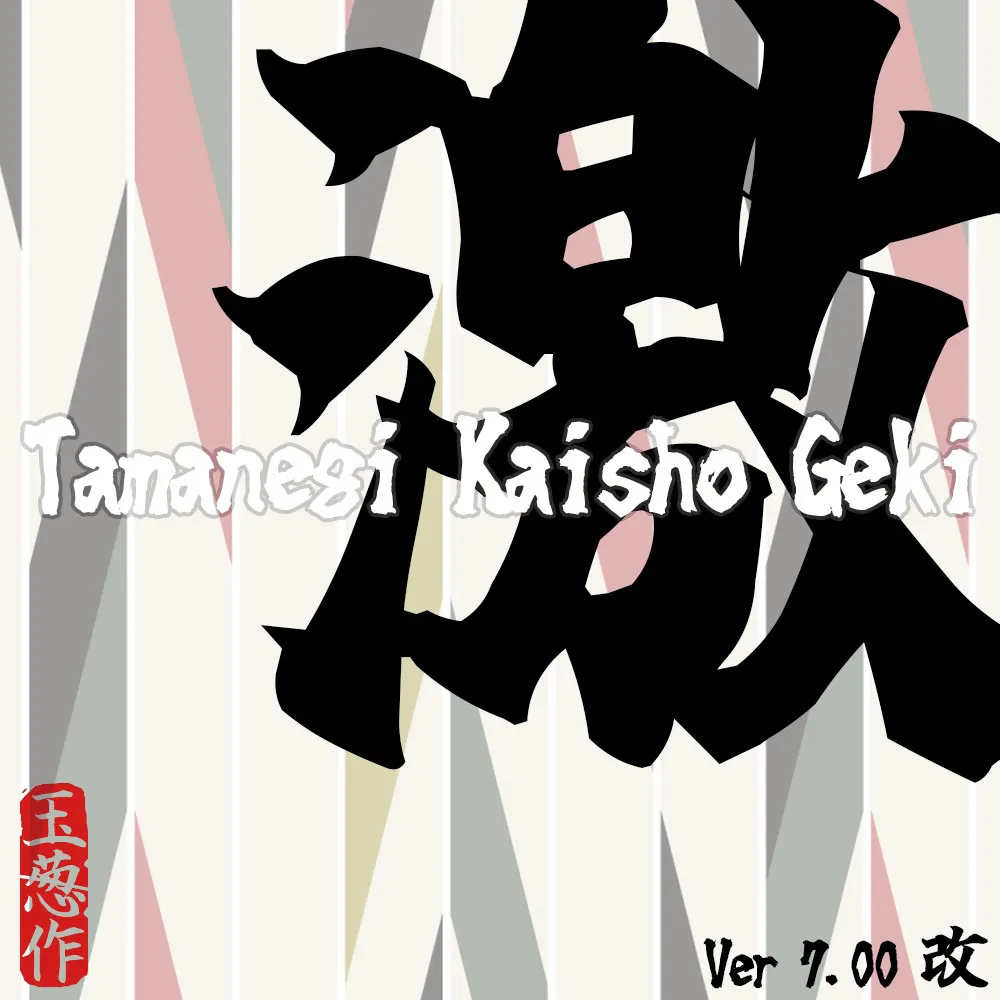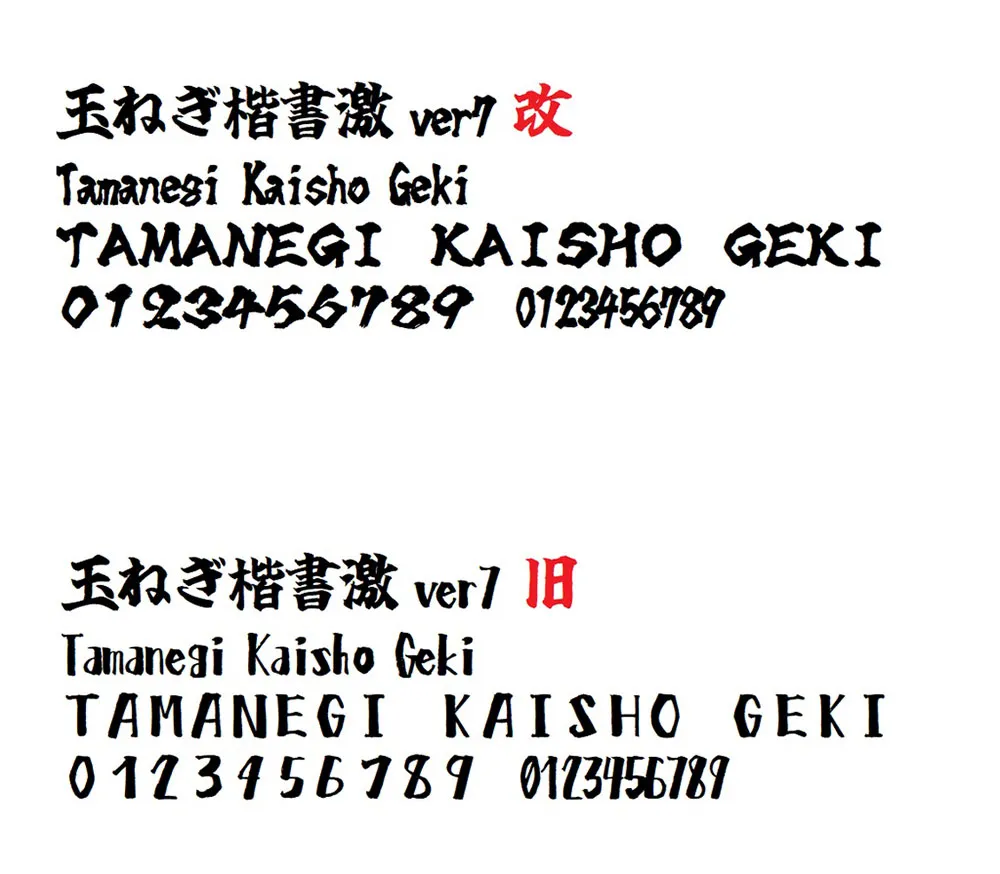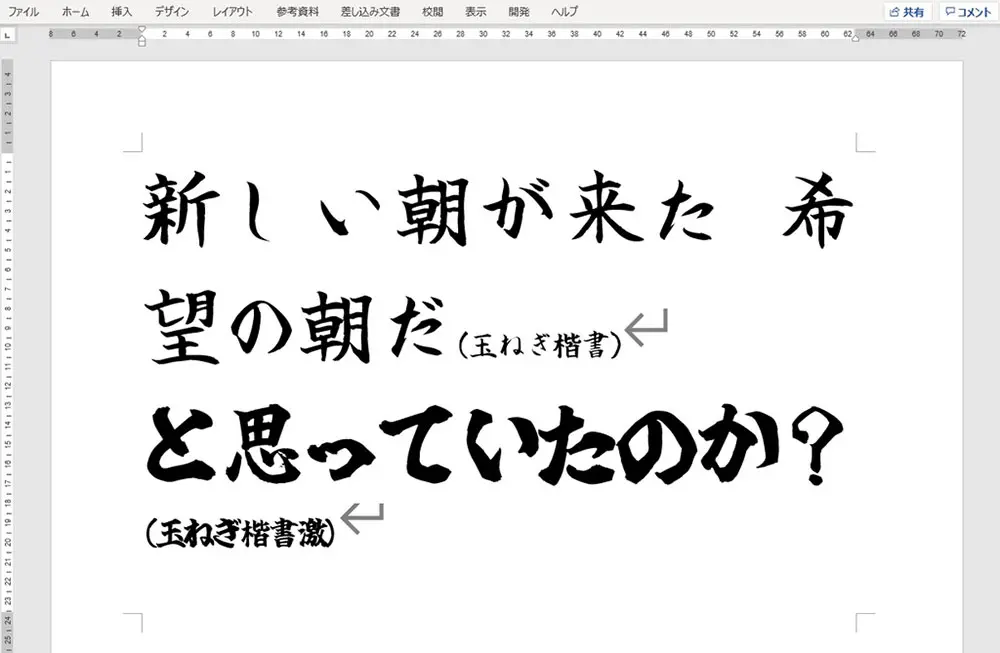
玉ねぎ楷書激無料版介紹
玉ねぎ楷書激無料版是通過使用武藏系統 (http://opentype.jp/) 的手寫字體創建的。是為動畫、同人誌、賀年卡等場景製作的簡單手寫毛筆字體洋蔥楷書(ttf形式)有點激烈。
這個字體是免費版(JIS第一水準漢字+α),目前正在製作JIS第二水準對應版。
本ファイルは武蔵システム(http://opentype.jp/)の 手書きでフォント を使って作成しました。動畫・同人誌・年賀狀などあらゆる創作の場面を想定して作られたシンプルな手書き毛筆フォント玉ねぎ楷書(ttf形式)をちょっと激しくしたものです。